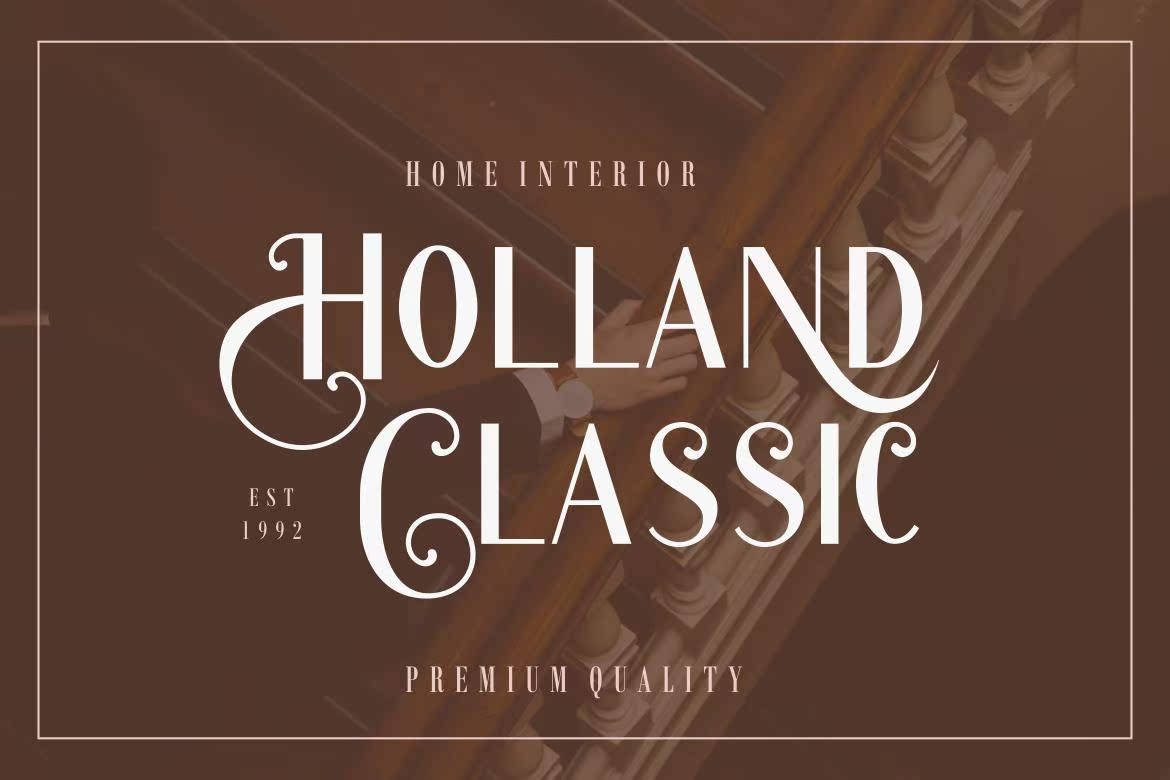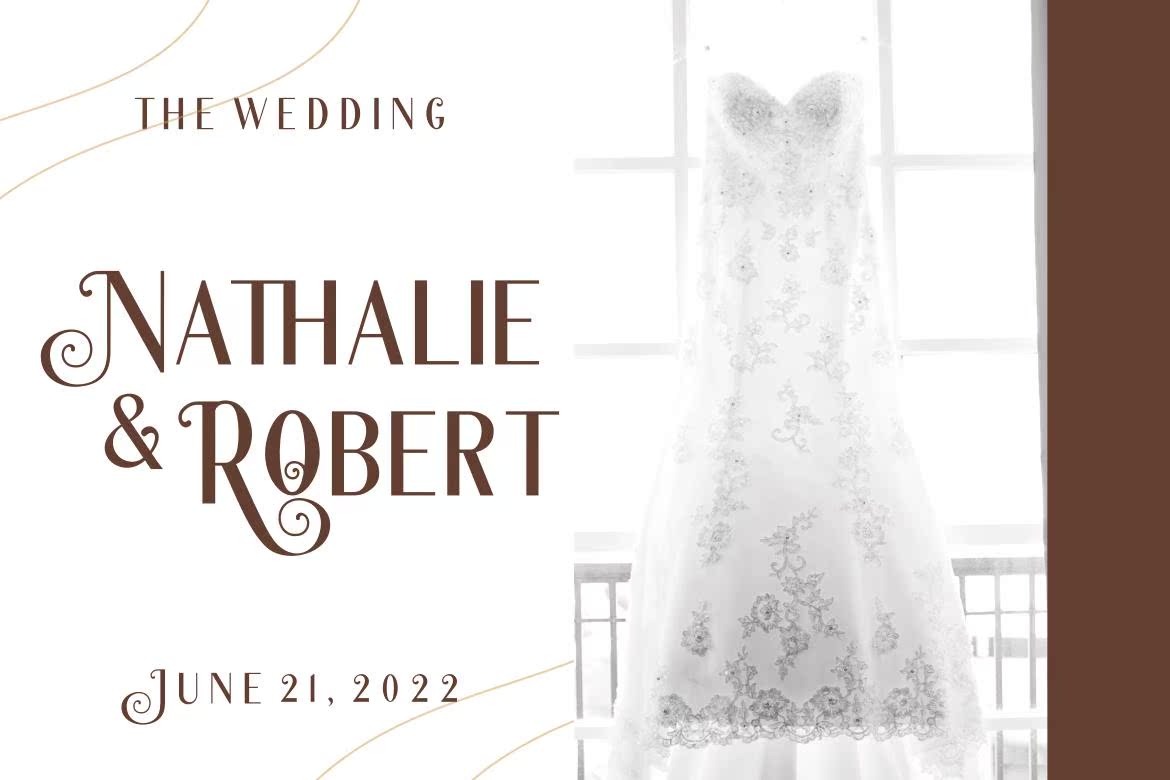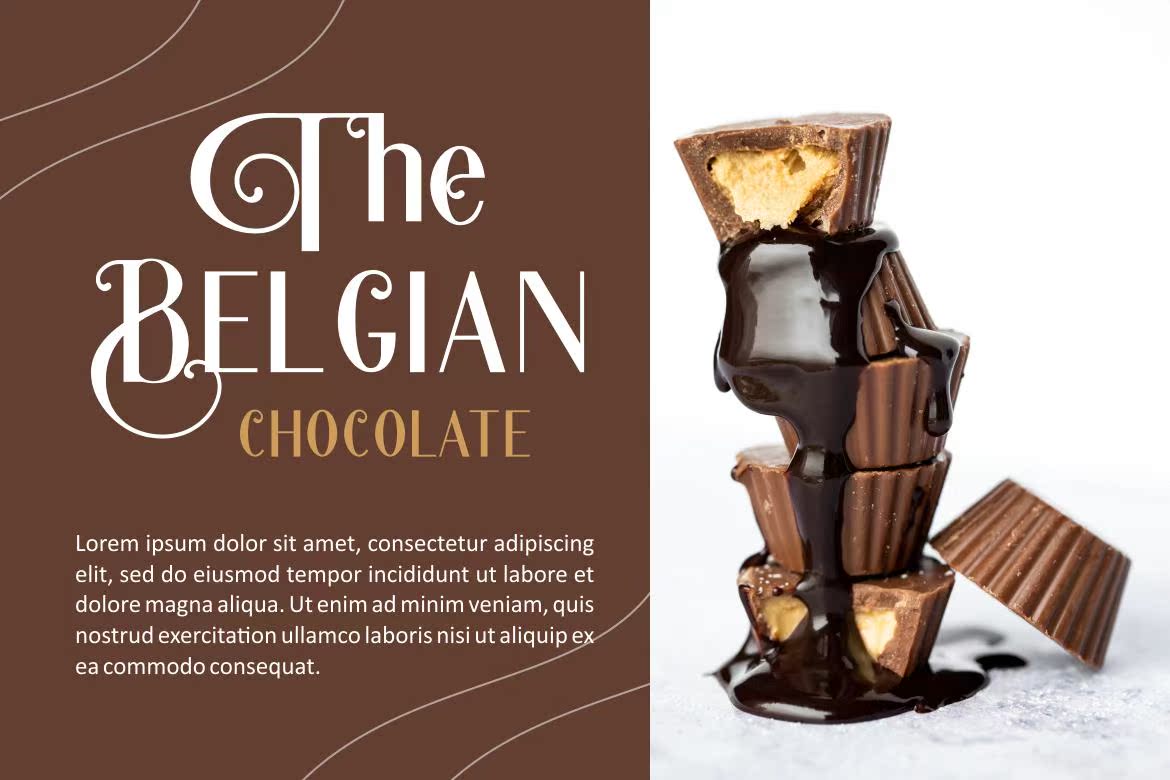
CrowsfontisasAnsserifcomewithwirlsyetethnicStyle。此字体适用于创建徽标、打印模板、海报、品牌、婚礼宣传、报价或任何内容。可用的2种样式字体:小写和小写字母。CrowsfontisasAnsserifcomewithwirlsyethnicStyle。此字体适用于创建徽标、打印模板、海报、品牌、婚礼宣传、报价、,oranythingelse.availablein2stylefont:lowercaseandallcaps。